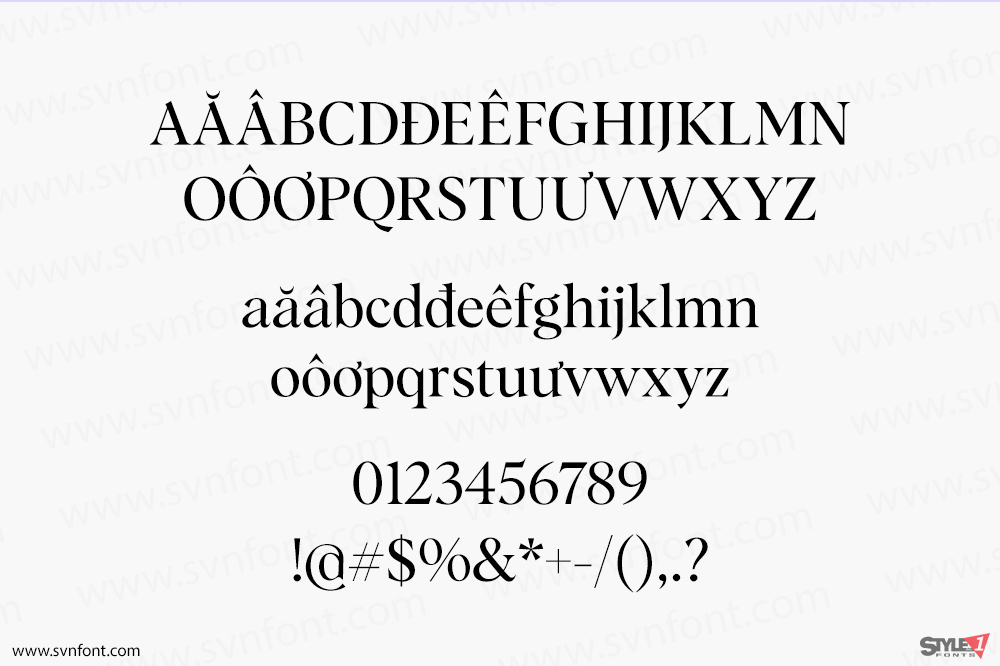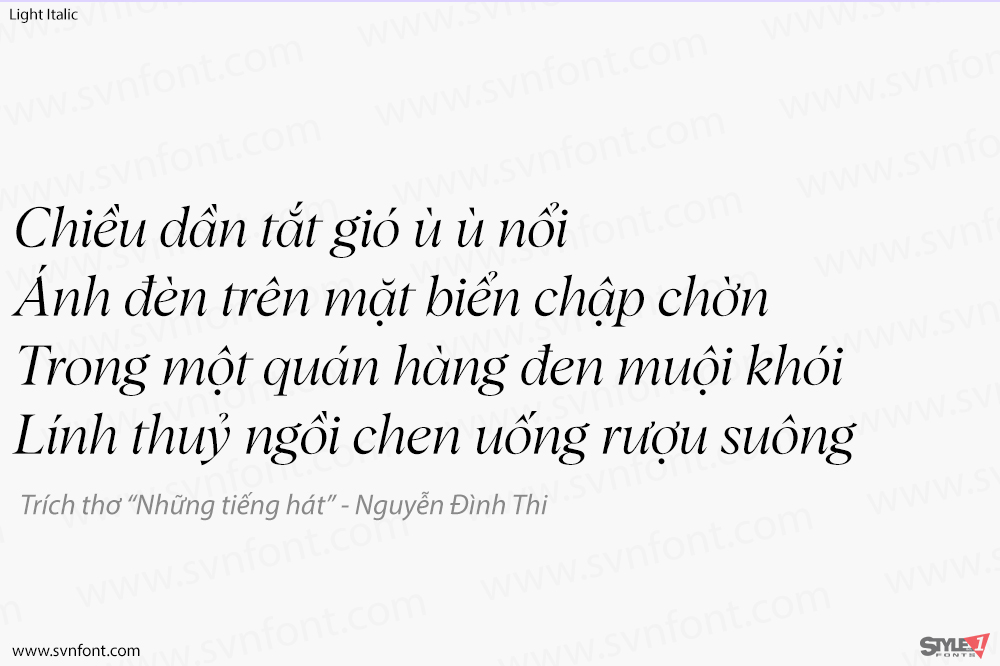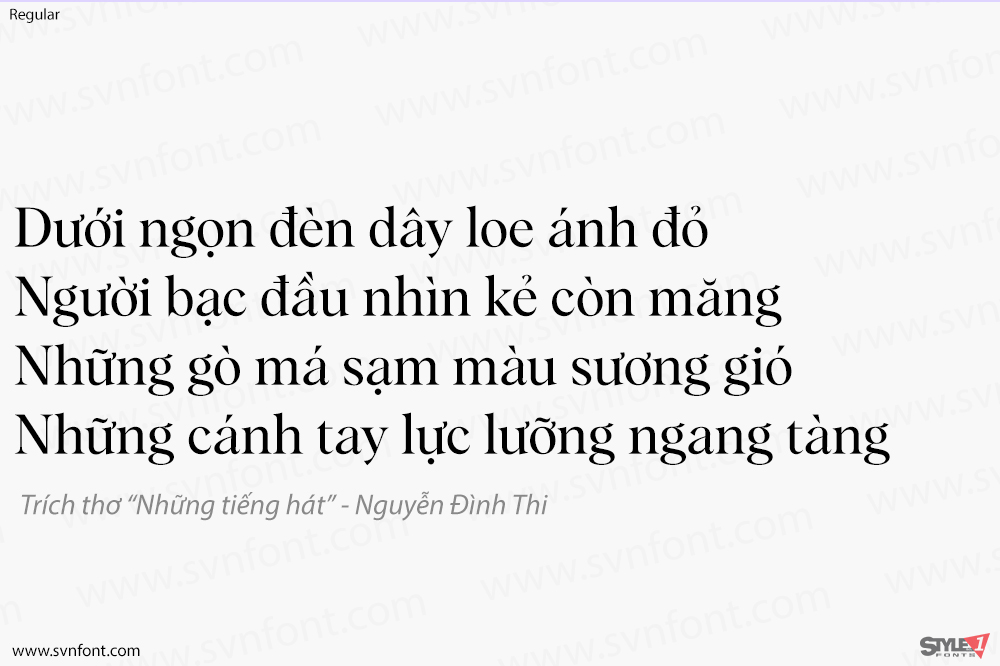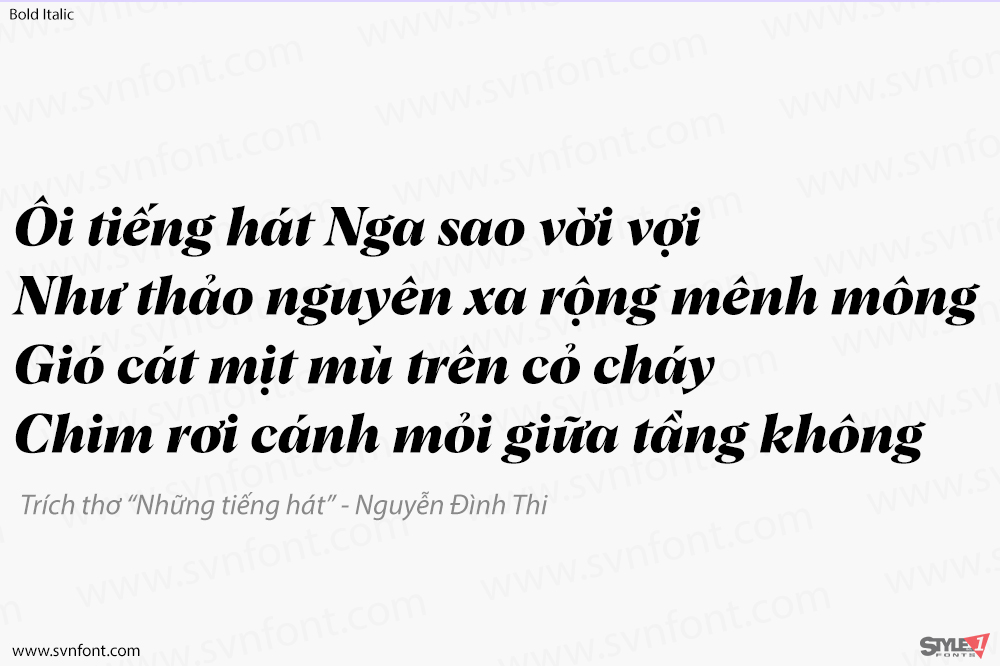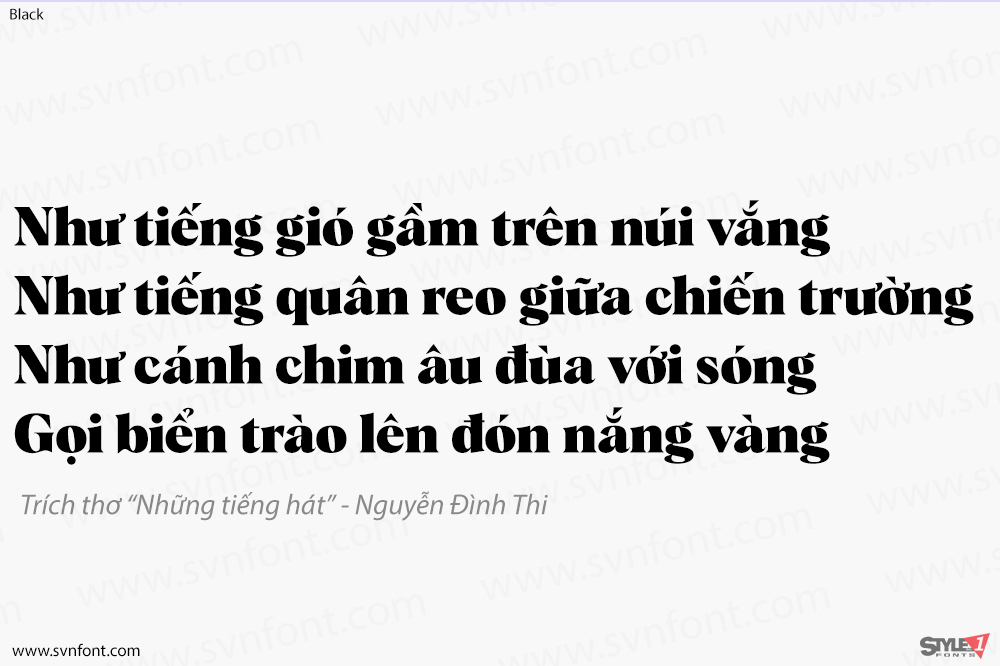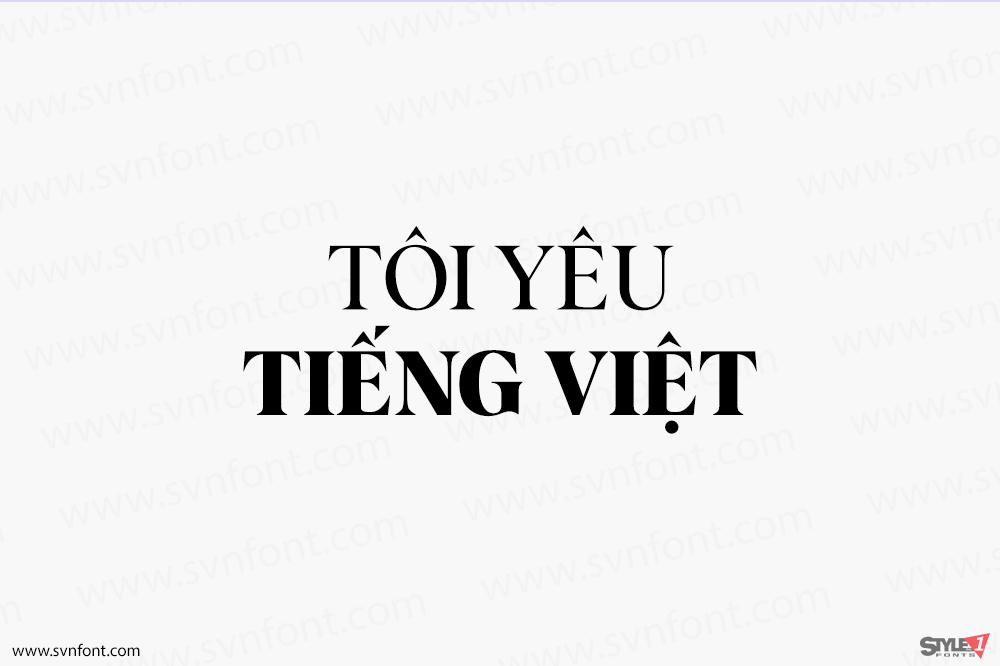
Họ phông chữ Albra của chúng tôi là một bộ sưu tập toàn diện cao cấp các kiểu chữ được thiết kế để phối hợp với nhau trong nhiều ứng dụng khác nhau. Từ các tiêu đề tinh tế đến ứng dụng văn bản nhỏ. Xây dựng thương hiệu, biên tập, bao bì hoặc logo. Một kiểu chữ “trâu cày” vượt thời gian với nhiều khả năng.